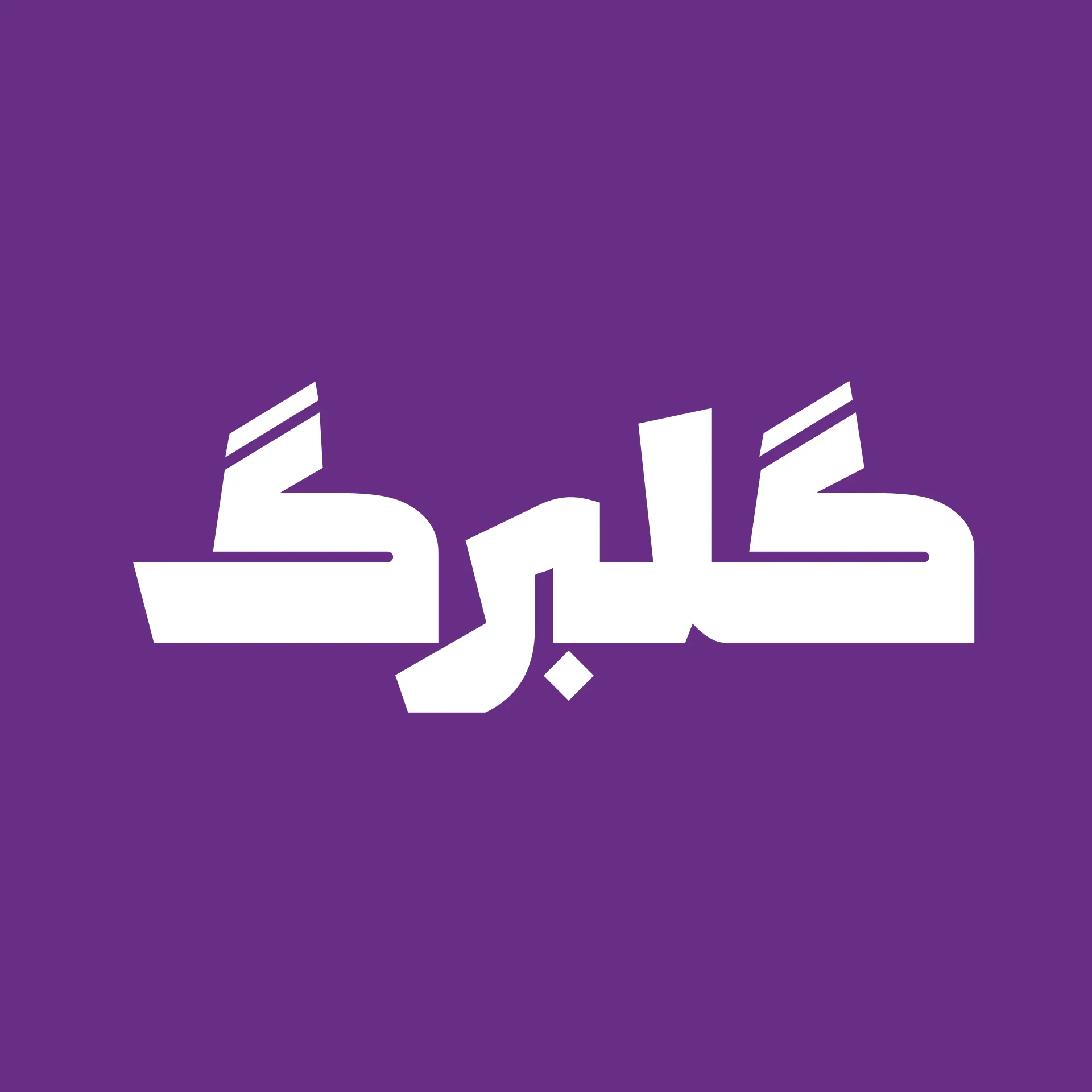
بعضی پروژهها نیاز به فونتی دارند که محکم، قدرتمند و چشمگیر باشد — فونتی که وقتی روی پوستر یا بنر مینشیند، از فاصله ۱۰ متری هم جلب توجه کند. فونت وزین (Vazin) دقیقاً برای همین لحظهها ساخته شده است.
فونت وزین؛ سنگین، هندسی، تأثیرگذار
فونت وزین یک تایپفیس نمایشی و سنگین است که برای تیترها و عبارتهای کوتاه طراحی شده. بهدلیل قدرت بصری بالا، در اندازههای بزرگ جلوه بیشتری دارد و میتواند پیام شما را با اقتدار به مخاطب منتقل کند.
این خانواده در سه استایل متفاوت ارائه شده که هر کدام شخصیت بصری خاص خود را دارند:
- استایل اول: ساختار هندسی خالص با خطوط صاف و زوایای تیز — مناسب برای طراحیهای مدرن و صنعتی.
- استایل دوم: نسخهای با گوشههای نرمتر و منحنیهای ملایم — برای پروژههایی که به قدرت همراه با لطافت نیاز دارند.
- استایل سوم: ترکیبی از دو استایل قبلی با جزئیات بیشتر — ایدهآل برای لوگوتایپ و برندینگ.
فونت وزین برای چه کاربردهایی مناسب است؟
- تیتر روزنامه و مجله: قدرت بصری وزین، تیترها را غیرقابل چشمپوشی میکند.
- پوستر و بیلبورد تبلیغاتی: در ابعاد بزرگ، این فونت بهترین عملکرد را دارد.
- طراحی جلد کتاب: مخصوصاً برای کتابهای ژانر هیجانی، معمایی و تاریخی.
- لوگو و برندینگ: برندهایی که میخواهند حس قدرت، اعتماد و استحکام را منتقل کنند.
- تیزر و موشن گرافیک: در رسانههای تصویری، سنگینی وزین توجه را به سرعت جلب میکند.
ترکیب فونت وزین با سایر فونتها
فونت وزین یک فونت کاملاً نمایشی است. برای بهترین نتیجه، آن را با فونتهای سادهتر و خنثیتر برای متن اصلی ترکیب کنید. پیشنهاد ما: